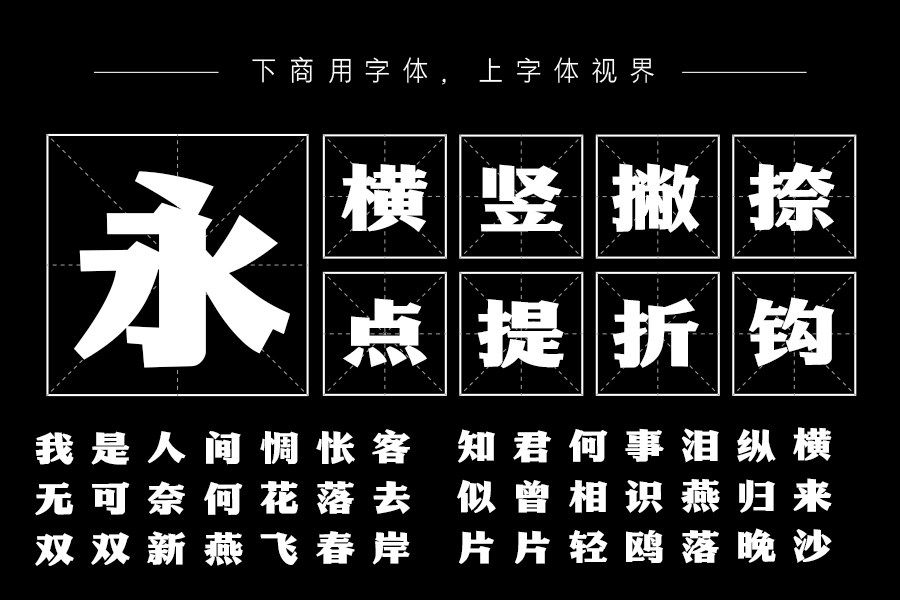
Aa黑宋是一款结合黑体和宋体的设计特征的字体,由Aa字库设计,其独特的设计特征突出了标题字体。这种字体的设计源于对传统宋体字体的推陈出新,将其与现代黑体字体相结合,创造出了一种全新的字体风格。
Aa黑宋的设计特征主要包括以下几个方面。首先,它拥有宋体字体的传统风格,其线条清晰,书写流畅,视觉效果舒适。其次,它融合了现代黑体字体的设计元素,使字体更加醒目、饱满,使得文章内容更具可读性。最后,Aa黑宋在字体形态上有所创新,不拘泥于传统的宋体字体形式,而加入了更多现代化的元素,使其在视觉上更为丰富多彩。
Aa黑宋的字体设计风格非常适合用于标题、宣传广告、画册设计等场合,能够让内容更加引人入胜,吸引读者的眼球,达到更好的传播效果。此外,Aa黑宋还可以应用于印刷媒介、数字媒体等领域,为设计师们提供了更多的选择。
总之,Aa黑宋的设计特征突出了标题字体,创新地结合了传统宋体字体和现代黑体字体,让其在字体设计领域具有了独特的地位。如果你需要一种既保留传统元素,又具有现代风格的字体设计,Aa黑宋将是你的不二选择。